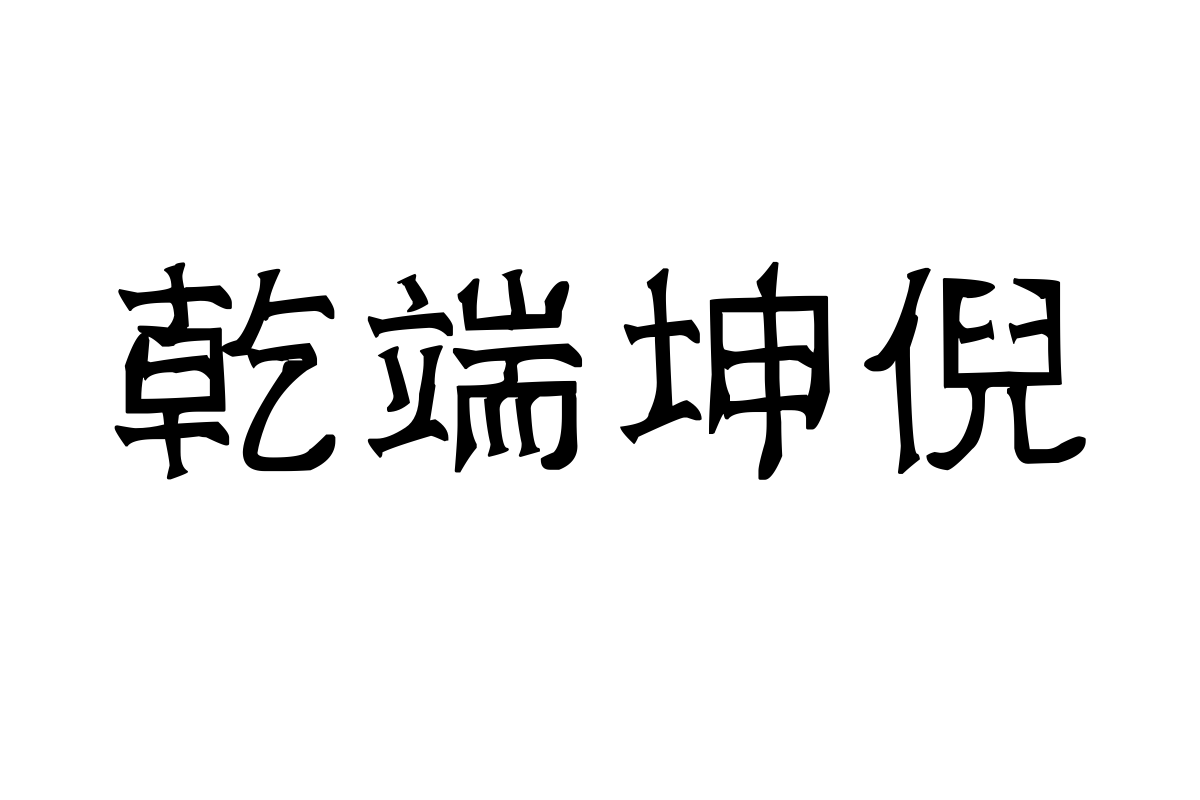
汉标碑石体字体是一种具有深厚历史和文化内涵的汉字书法字体,它源自汉代的碑文刻石,因此得名。这种字体的特点主要体现在以下几个方面:
1. 结构严谨:汉标碑石体的字形结构非常严谨,笔画粗细有度,线条流畅有力,具有很强的视觉冲击力和艺术美感。
2. 风格古朴:汉标碑石体的字体风格古朴典雅,线条简练,笔画圆润,给人一种庄重、肃穆的感觉。
3. 韵味十足:汉标碑石体的字体韵味十足,既有隶书的刚劲有力,又有草书的飘逸灵动,体现了汉代文化的精髓。
4. 易于辨识:由于汉标碑石体的字形结构独特,笔画特点鲜明,因此非常容易被人们辨识和记忆,是学习和研究汉字书法的重要参考。
5. 传承有序:汉标碑石体字体在历史上一直受到人们的推崇和学习,其传承有序,对后世的汉字书法产生了深远影响。
总之,汉标碑石体字体以其独特的风格和韵味,成为了汉字书法史上的一个重要组成部分,对于研究汉字书法艺术具有重要的价值。